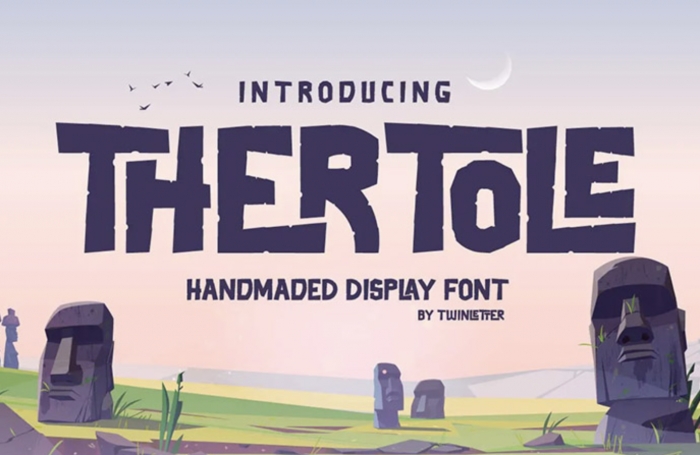
Il mondo variegato e fantastico del cinema ha naturalmente bisogno estremo di una comunicazione che colpisca direttamente la fantasia dello spettatore.
Per farlo gli autori pensano da sempre a locandine e covers che possano diventare una vetrina assoluta verso quella particolare pellicola. Queste immagini sapientemente montate uniscono tra loro i protagonisti dei film, le azioni ed i momenti stessi che sono contenuti nel lungometraggio.
Capita altre volte che sia il font stesso inserito nella locandina a diventare il vero protagonista ecco perché la scelta di un carattere piuttosto che un altro diventa molto impostante. In questa raccolta di 30 e oltre fonts da usare in locandine di films e covers sono stati selezionati caratteri davvero potenti e sapientemente pensati per essere la base di progetti da realizzare appositamente.